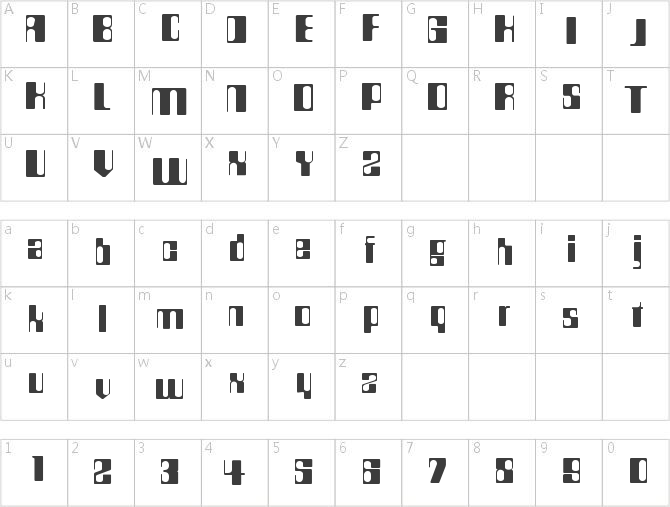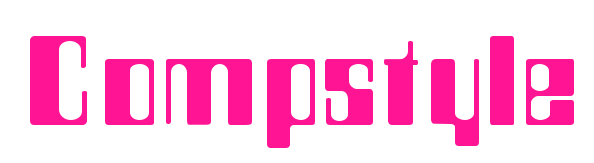
Compstyle 詳情頁(yè)
字體名稱: Compsty
Compstyle
Compstyle字體字庫(kù)是一款讓人賞心悅目、百看不厭的英文字體,適合各類廣告和產(chǎn)品包裝設(shè)計(jì)應(yīng)用,字體大小0.04MB,格式為ttf字體,上傳用戶是@小咖,作者/版權(quán)方為未知